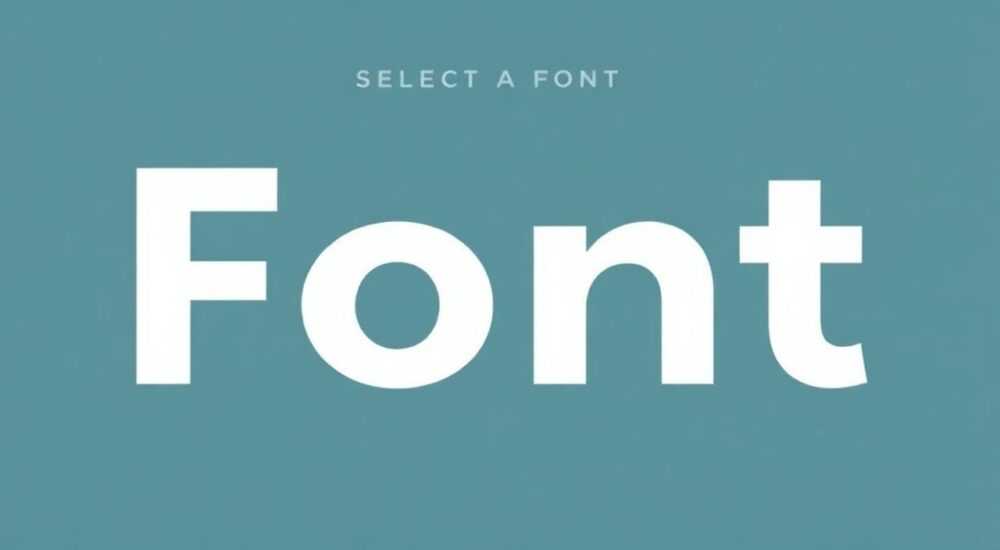
Как выбрать шрифт в фотошопе
Выбор шрифта в Photoshop — это не просто прихоть дизайнера, а важный этап создания визуально сильной и функциональной композиции. От правильного выбора зависит читаемость, настроение проекта и восприятие бренда. Важно учитывать контекст, целевую аудиторию, технические ограничения и эстетические принципы.
Современные версии Adobe Photoshop предоставляют доступ к тысячам шрифтов через Adobe Fonts, а также позволяют использовать локальные и веб-шрифты. Однако обилие вариантов может вызвать растерянность даже у опытных пользователей. Эта статья поможет разобраться в типах шрифтов, научит выбирать их по контексту, покажет, как эффективно работать с панелью шрифтов и избегать типичных ошибок. Мы рассмотрим практические шаги, экспертные рекомендации и актуальные тенденции 2026 года, чтобы ваш выбор был не только красивым, но и стратегически обоснованным.
Типы шрифтов и их особенности
Шрифты делятся на несколько основных категорий, каждая из которых несёт определённую смысловую нагрузку. Понимание этих различий помогает делать осознанный выбор. Основные группы: засечковые (serif), беззасечковые (sans-serif), рукописные (script), декоративные (display) и моноширинные (monospace).
Засечковые шрифты, такие как Times New Roman или Georgia, имеют небольшие черточки на концах букв. Они ассоциируются с традицией, надёжностью и академичностью. Часто используются в печатных СМИ, книгах и официальных документах. Беззасечковые шрифты, например Helvetica или Roboto, выглядят современно и минималистично. Их выбирают для цифровых интерфейсов, рекламы и брендирования.
Рукописные шрифты имитируют человеческий почерк. Они добавляют индивидуальность, тепло и эмоциональность. Подходят для свадебных приглашений, логотипов крафтовых брендов или рекламы в нишевых нишах. Декоративные шрифты — это яркие, стилизованные начертания, которые сразу привлекают внимание. Но их стоит использовать с осторожностью: они плохо читаются при большом объёме текста.
Моноширинные шрифты, такие как Courier или Fira Code, имеют одинаковую ширину каждого символа. Традиционно применяются в коде, технической документации и визуальных проектах с цифровой эстетикой.
Когда какой тип использовать?
- Заголовки в интернет-магазине — лучше выбирать чистые sans-serif шрифты: они быстро воспринимаются и хорошо работают на мобильных устройствах.
- Книжная обложка классики — подойдут засечковые шрифты с высокой контрастностью, например Garamond или Baskerville.
- Приглашение на вечеринку — можно использовать script или display шрифты, но только если они остаются читаемыми.
- Интерфейс приложения — предпочтительны системные или open-source шрифты, такие как Inter, Open Sans или SF Pro, обеспечивающие доступность и масштабируемость.
Тип шрифта |
Ассоциации |
Примеры |
Где использовать |
Засечковые |
Традиция, авторитет, стабильность |
Times New Roman, Georgia, Playfair Display |
Печатные издания, корпоративные отчёты, сайты новостей |
Беззасечковые |
Современность, простота, технологичность |
Helvetica, Arial, Montserrat |
Веб-сайты, мобильные приложения, презентации |
Рукописные |
Личность, творчество, эмоции |
Lobster, Pacifico, Caveat |
Логотипы, открытки, соцсети |
Декоративные |
Яркость, уникальность, игривость |
Bubblegum Sans, Bebas Neue |
Постеры, баннеры, детские проекты |
Моноширинные |
Техника, точность, нейтральность |
Courier, Consolas, Space Mono |
Код, технические интерфейсы, хайтек-дизайн |
Как выбрать шрифт по контексту и цели проекта
Главное правило: шрифт должен служить содержанию, а не затмевать его. Перед тем как кликнуть на список шрифтов, задайте себе три вопроса: кто целевая аудитория? Какова цель сообщения? Где будет использоваться макет?
Если вы создаёте рекламу для молодёжного бренда одежды, уместны современные геометрические sans-serif шрифты с высокой ударностью — например, Poppins или Raleway. Для финансового отчёта подойдёт сдержанный засечковый шрифт с хорошей читаемостью, такой как Lora или Merriweather.
Целевая платформа тоже имеет значение. На экранах смартфонов плохо читаются мелкие засечки и тонкие линии. Поэтому для мобильных проектов выбирайте шрифты с увеличенным x-height (высотой строчных букв) и хорошей межбуквенной регулировкой. В 2026 году особенно популярны адаптивные шрифты, которые автоматически меняют вес и ширину в зависимости от размера экрана.
Пошаговый алгоритм выбора шрифта
- Определите тон коммуникации: серьёзный, дружелюбный, люксовый, игривый.
- Уточните формат использования: печать, веб, видео, соцсети.